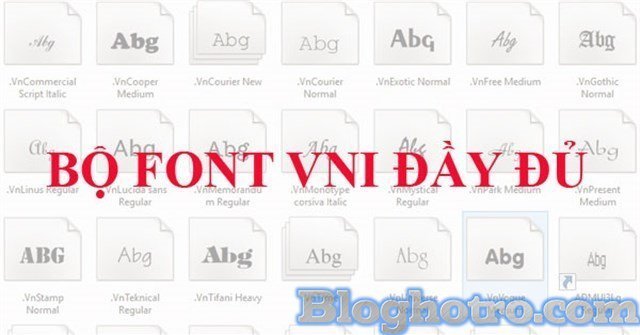
Giới thiệu Font chữ VNI
Hiện nay thì phông chữ VNI là một trong những bộ có các phông chữ đầy đủ nhất dành cho các bạn muốn sử dụng để gõ tiếng việt. Ngoài ra thì tại đây các bạn cũng có thể tìm thấy cho mình những font chữ khi viết rất độc đáo và lạ mắt mà chỉ khi nào tải về các bạn mới có thể tự mình trải nghiệm được hết tất cả các kiểu dáng của các dạng phông chữ này
Đối với Font chữ VNI khi cài đặt về máy tính laptop, pc của những người thường xuyên tải những tài liệu như MS Word từ internet về cực kỳ hữu ích bởi bộ phông chữ này đầy đủ điều kiện và đáp ứng yêu cầu nhập văn bản của các file dữ liệu download về này. Với một bộ full các phông như vậy thì ngoài việc đáp ứng như cầu không bị vỡ chữ hay lỗi chữ thì còn có rất nhiều lựa chọn từ kiểu dáng, kích cỡ nghệ thuật cực kỳ đẹp mắt đối với những người sử dụng
Việc bạn sử dụng font VNI là điều hoàn toàn cần thiết để tránh khỏi những rắc rối khi thiếu các phông chữ gây ra thì mình khuyên các bạn nên sử dụng nó. Về việc khả năng tương thích của nó thì thời buổi công nghệ thông tin rồi nên cập nhật của VNI đối với các hệ điều hành máy tính trở nên tốt hơn các bạn có thể sử dụng đối với mọi hệ điều hành
Tính năng chính của Font VNI
- Hỗ trợ thiết bị 300 các loại phông chữ, kiểu chữ hoàn toàn khác nhau
- Các phông chứ được thiết kế đẹp cho người dùng
- Tối ưu dung lượng, thân thiện đối với mọi thiết bị